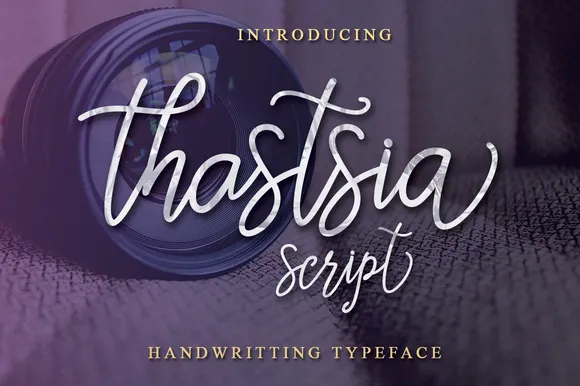
Thastsia Script Font – Download Grátis
Descubra Thastsia Script, uma linda fonte à mão escrita que oferece um toque de linha monoliné especializado para projetos de arte tipográfica de alto nível. Esse design cuidadosamente criado pelo designer Gfont oferece um conjunto atraente de opções de layout que permitem aos designers criar trabalhos artísticos impressionantes com facilidade. A Thastsia Script é uma fonte script capaz de imprimir uma impressão única, mas também apresenta recursos extras para tornar o processo ainda mais versátil e criativo. Seja você um designer profissional ou iniciante, Thastsia Script traz alegria à sua arte digital com seu toque diferenciado e facilidade de uso. Experimente hoje e inspire-se com uma fonte que se destaca em sua próxima criação artística.